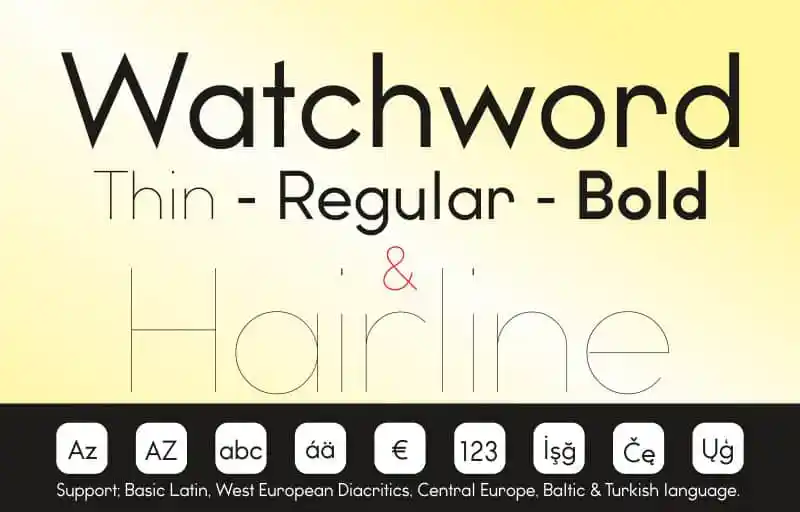
Watchword Sans Serif Font – Download Grátis
Watchword Sans Serif é uma nova fonte geométrica sans-serif que se destaca no design moderno do web. Desenvolvida para ser facilmente utilizada em qualquer lugar da sua página, seja ela um blog pessoal ou uma estruturada empresa online. A característica mais interessante de Watchword é seu aspecto alegre e jovial, tornando-a perfeitamente adaptável para uso por agências digitais e criativas. Este estilo energético e cheio de vida é especialmente propenso para atender aos consumidores millennials, uma faixa etária que valoriza o design moderno e o bom humor. Ideal para marcar presença na web, Watchword Sans Serif oferece um tom acolhedor e versátil, perfeito tanto para websites quanto para designs gráficos de produtos ou publicidade digital.